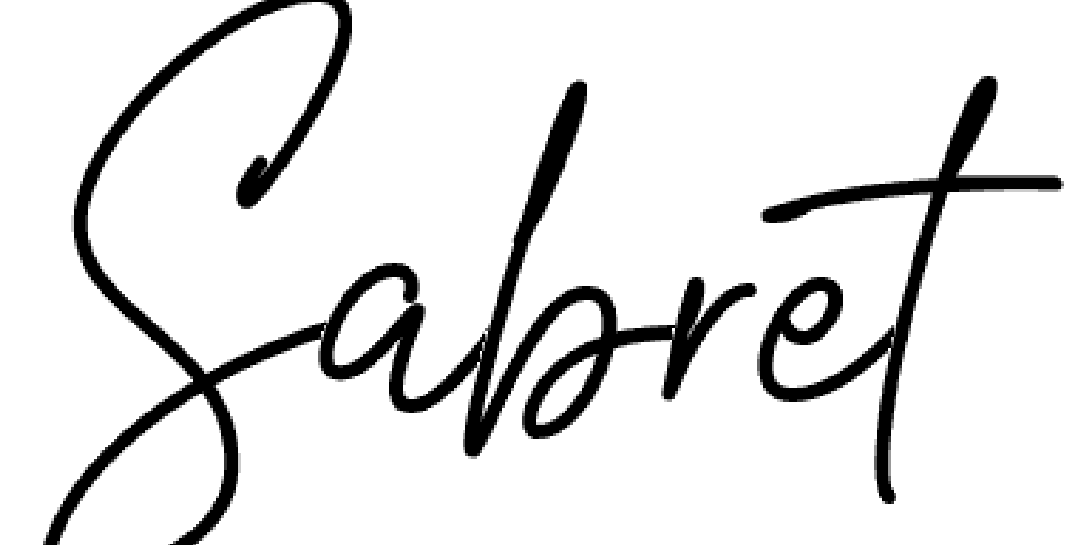
Bu font nedir bulamıyorum?
Merhaba bu yazı fontunu arıyorum birebir aynısını bilen varmı?
Sanırım bu.
Signature style / imza fontu” kategorisine giriyor
• Signatura Monoline
• Brittany Signature
• Allura
• Playlist Script bunları deneyebilirsin.
Grayscale Signature () buyur hocam